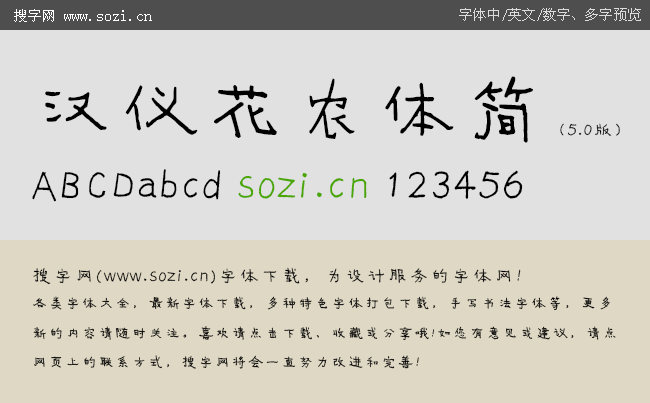
漢儀花農(nóng)體簡(jiǎn)5.0版
搜字網(wǎng)提供一款漢儀花農(nóng)體簡(jiǎn)中文藝術(shù)字體下載,漢儀花農(nóng)體是一款卡通風(fēng)格的創(chuàng)意藝術(shù)字體。此款字注重率性表達(dá),書(shū)寫(xiě)一氣呵成,文字透出古拙大方兼有雅致的文人氣息。適宜文化、新聞以及商業(yè)等領(lǐng)域使用等。